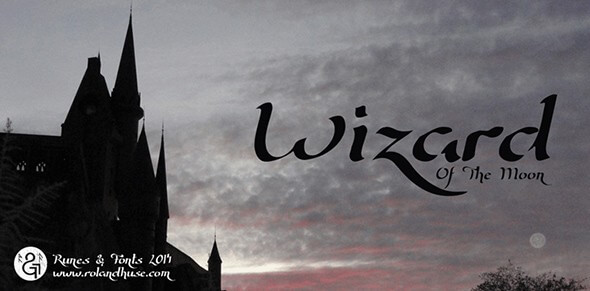
中世風の無料フォント20選|本・ポスター・ゲームに使えるゴシック書体まとめ
中世風の無料フォントを探している方に向けて、本やポスター、グラフィック、ゲーム制作などに使える個性的な「中世・ゴシック(ブラックレター)系」のフリーフォントを集めました。荘厳な雰囲気やファンタジー感を演出したいプロジェクトにぴったりのフォントばかりです。気になったものを下のリストからチェックして、デザインに取り入れてみてください。
ここで紹介するフォントは、書籍・ポスター・ロゴ・ゲームのタイトルロゴなど、幅広い用途に合わせやすいデザインを持っています。装飾的な飾り文字や独特の字形を含むものが多く、1書体加えるだけでプロジェクトの世界観をぐっと引き締めてくれます。
Royal by Aldus
Royal by Aldus 中世風フォント
Salterio Shadow by Intellecta Design
ゴシック体からインスパイアされたこのフォントは、無料で利用できます。配布ページでは非商用プロジェクト向けとされているため、商用で使いたい場合はライセンス表示を確認しましょう。
Salterio Shadow by Intellecta Design ゴシック体フォント
Kingthings Spikeless by Kingthings
Kingthings Spikeless by Kingthings 中世風フォント
Celtic by Sam Wang
Celtic by Sam Wang ケルト風フォント
Germanika Personal Use by Billy Argel
Germanika Personal Use by Billy Argel ゴシック体フォント
Fette UNZ Fraktur by Peter Wiegel
フラクトゥール(ドイツの伝統的な書体様式)をベースにした斬新なデザインです。配布ページの記載では個人・商用の両方に使えるとされていますが、利用前にライセンス表示を確認しましょう。
Fette UNZ Fraktur by Peter Wiegel フラクトゥールフォント
Walk Da Walk Two by Måns Grebäck
Walk Da Walk Two by Måns Grebäck 中世風フォント
AuldMagik by AgaSilva
AuldMagik by AgaSilva ゴシック体フォント
Vlad TyepesⅡ(Vlad’s Dad) by Bolt Cutter Design
Vlad Tyepes II by Bolt Cutter Design 中世風フォント
Wizard Of The Moon by Runes&Fonts
手書き風・カリグラフィー風の趣がある書体です。利用にあたっては作成者の許可やライセンス条件が必要になる場合があるため、配布ページの記載を確認しましょう。
Wizard Of The Moon by Runes&Fonts カリグラフィー風フォント
DK Northumbria by David Kerkhoff
中世からインスパイアされた装飾的なフォントで、タイトルや見出しに使うと存在感を発揮します。ダウンロード時にライセンス条件を確認してから利用しましょう。
DK Northumbria by David Kerkhoff 中世風フォント
Gothic Leaf by Lord Kyl MacKay
2種類のスタイルがセットになったフォントです。配布ページの記載では個人・商用の両方に使えるとされていますが、利用前にライセンス表示を確認してください。
Gothic Leaf by Lord Kyl MacKay ゴシック体フォント
MagicMedieval by Dave Howell
MagicMedieval by Dave Howell 中世風フォント
Traditional Gothic, 17th c. by Lord Kyl MacKay
17世紀の伝統的なゴシック体を思わせる書体です。無料でダウンロードでき、配布ページの記載では個人・商用の両方に使えるとされています。利用前にライセンス表示を確認してください。
Traditional Gothic 17th c. by Lord Kyl MacKay ゴシック体フォント
FancyText by Diogene
他と一線を画す装飾的なデザインのフォントで、無料でダウンロードできます。利用にあたっては配布ページのライセンス記載を確認しましょう。
FancyText by Diogene 装飾フォント
Charakterny by Gluk
Charakterny by Gluk 中世風フォント
Black Letter by Angst
その名の通りブラックレター(中世のゴシック書体)を思わせる目立つデザインで、プロジェクトに取り入れると個性的な仕上がりになります。利用前にライセンス記載を確認しましょう。
Black Letter by Angst ブラックレターフォント
Your Royal Majesty by sharkshock
Your Royal Majesty by sharkshock 中世風フォント
CamelotCaps by House of Lime
中世からインスパイアされた大文字主体のフォントで、見出しやロゴに向いています。配布ページでは個人利用向けとされているため、商用利用の可否はライセンス表示を確認してください。
CamelotCaps by House of Lime 中世風フォント
MedievalAlphabet by House of Lime
緻密で装飾的なデザインが特徴のフォントです。無料でダウンロードでき、配布ページでは個人利用向けとされています。商用利用の可否はライセンス表示を確認してください。
MedievalAlphabet by House of Lime 中世アルファベットフォント
中世風フォントを使うときのポイント
中世・ゴシック系のフォントは装飾性が高く独特の字形を持つため、扱い方にいくつかコツがあります。
見出しやロゴに使う
ブラックレターや装飾的な書体は、本文(長文)に使うと可読性が下がりがちです。タイトルロゴ、見出し、看板、章扉など、短く目立たせたい箇所に使うのがおすすめです。
大文字・小文字の見え方を確認する
中世風フォントは大文字が華やかに装飾され、小文字がシンプルなものが多くあります。実際に使いたい文字列を入力してプレビューし、字形のバランスを確認してから採用しましょう。
日本語との組み合わせ
ここで紹介したフォントはいずれも欧文(ラテン文字)用です。日本語と組み合わせる場合は、雰囲気の合う和文フォントを別途用意し、欧文部分だけにこれらのフォントを充てると世界観がまとまりやすくなります。
Q. 日本語には対応していますか?
A. 今回紹介したフォントは欧文(ラテン文字)専用です。日本語の表示には対応していないため、和文には別のフォントを使い、欧文部分のデザインにこれらを活用するのが基本となります。
まとめ
中世・ゴシック(ブラックレター)系の無料フォントを20種類紹介しました。荘厳さやファンタジー感を演出したい本・ポスター・ゲーム・ロゴなどのプロジェクトに、こうした書体は強い個性を与えてくれます。気になったものを実際にダウンロードして、使いたい文字でプレビューしながら選んでみてください。利用前には、フォントごとに異なるライセンス条件を各配布ページで確認することを忘れないようにしましょう。